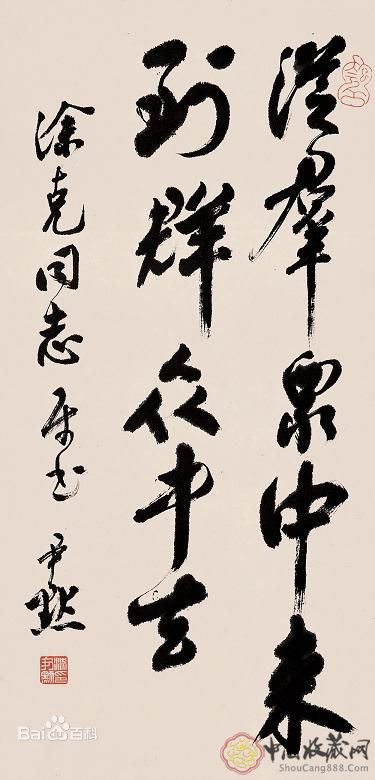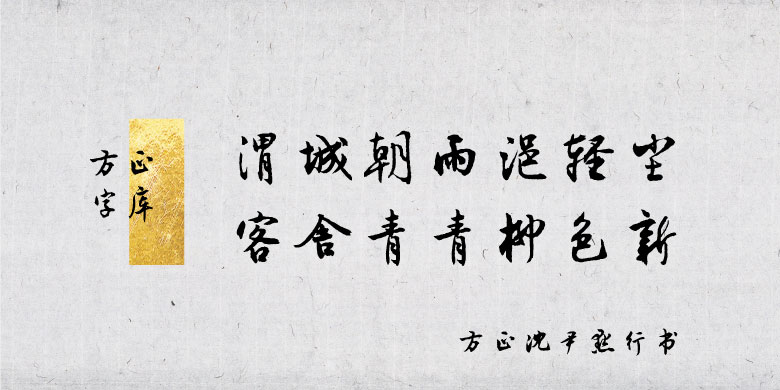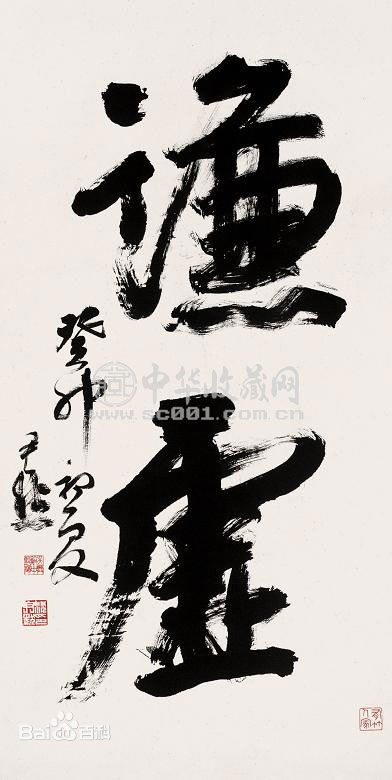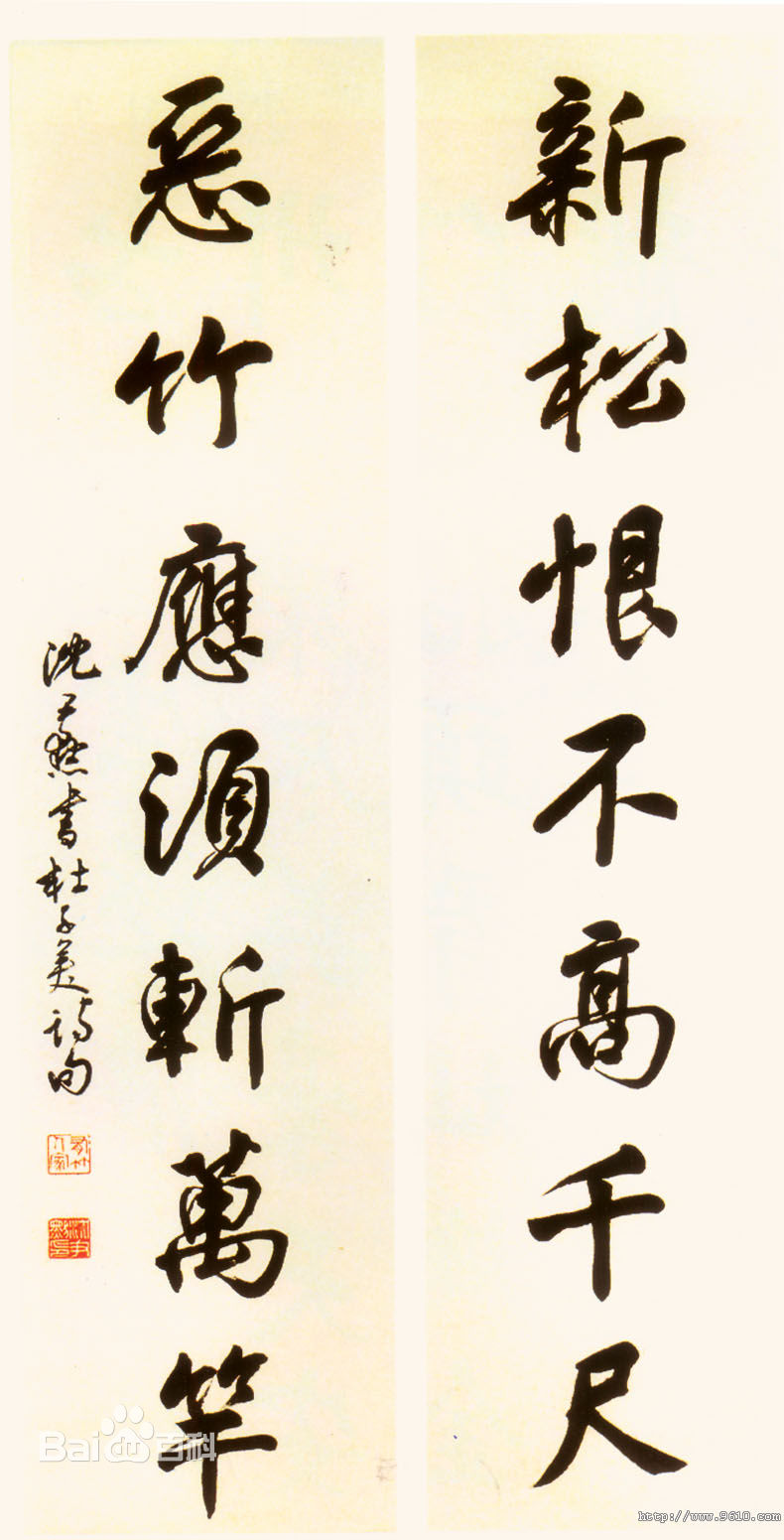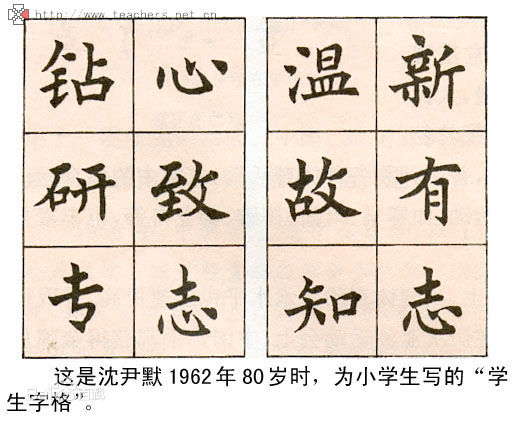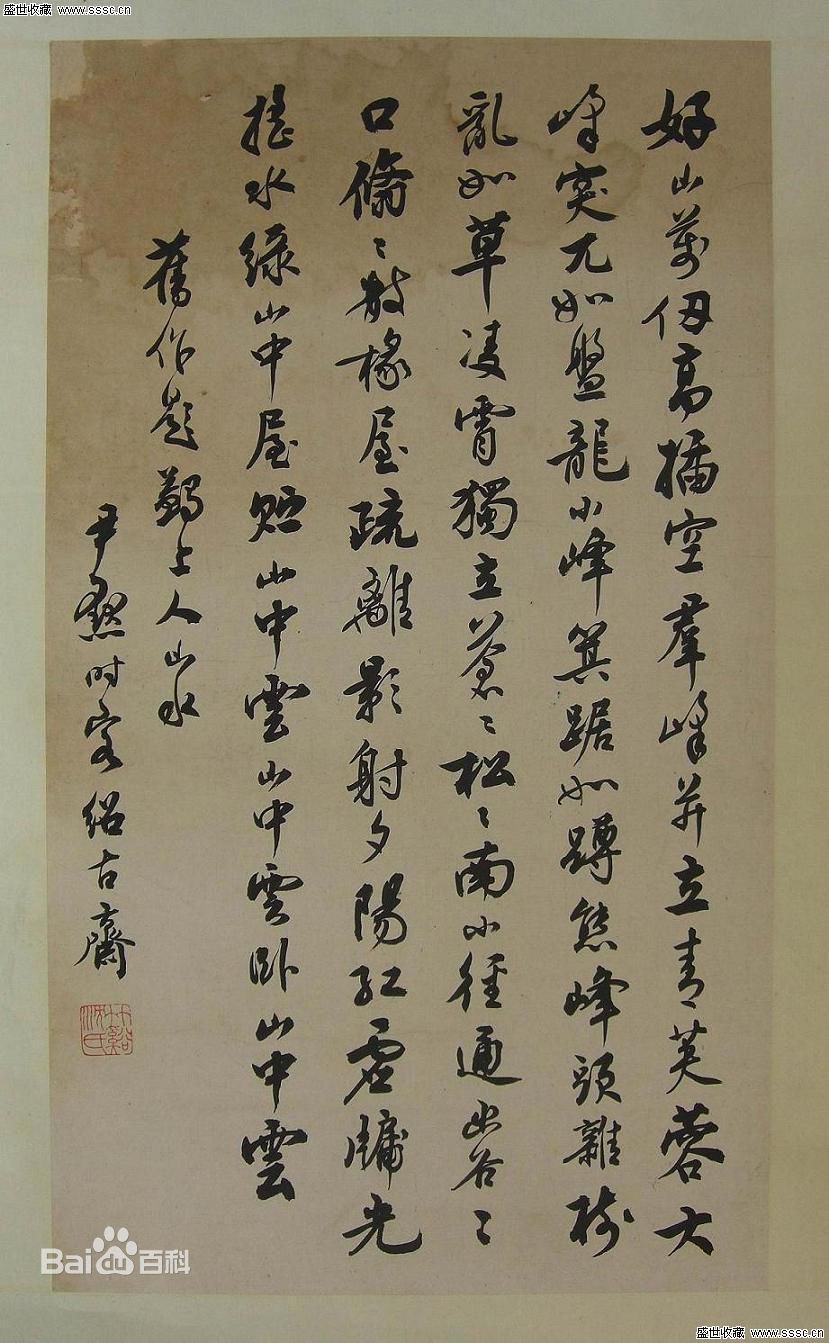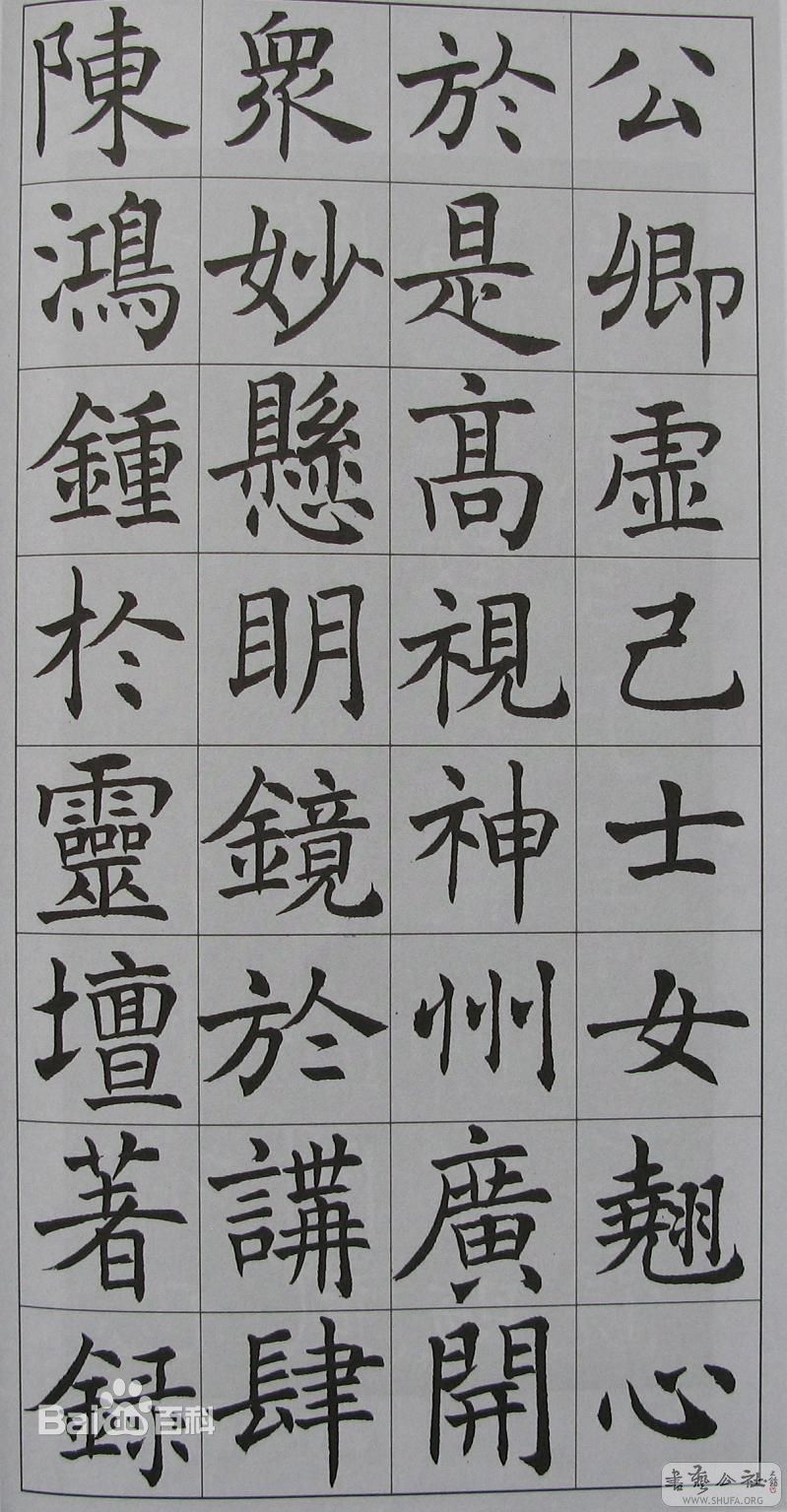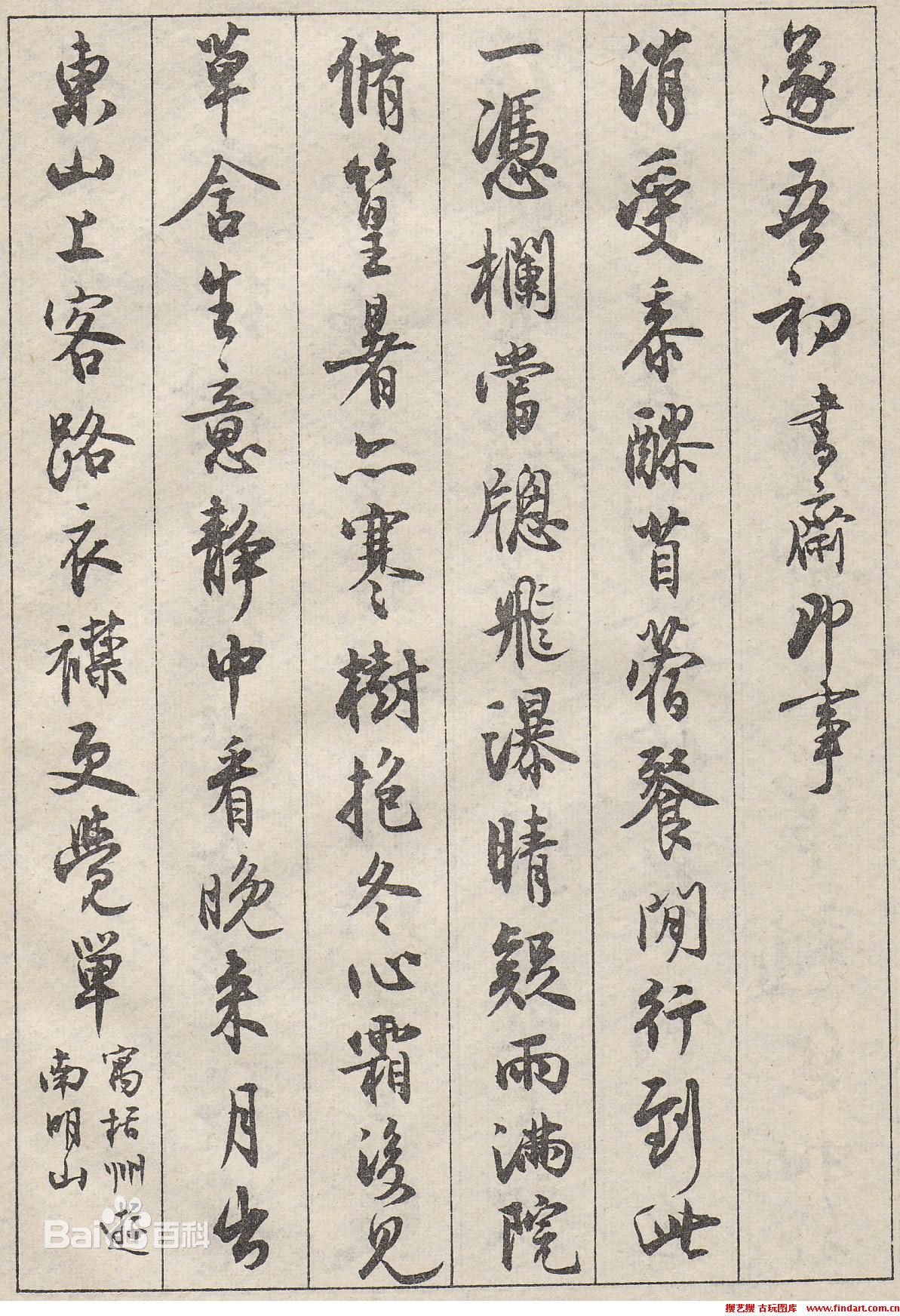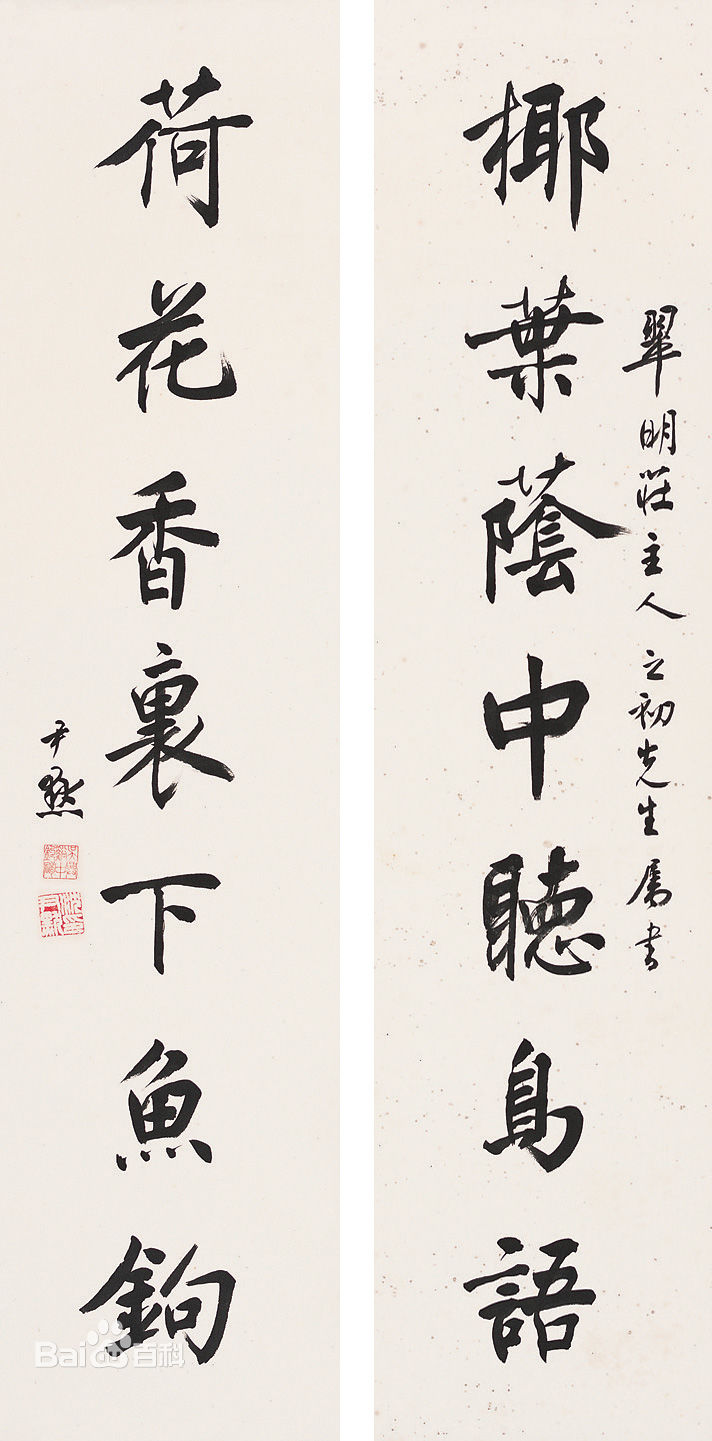
方正沈尹默行书 简
字体介绍:
沈尹默(1883-1971),当代书法家、诗人。原名君默,字中,号秋明,浙江吴兴(今湖州市)人。早年曾留学日本,解放前曾任北京大学文学系教授,北平大学校长。建国后任中央文史馆副馆长等,上海市人民委员会委员,第三届全国人大代表。工正行草书,由以行书著名。初学褚遂良,后遍习晋、唐诸名家,晚年融会苏轼、米芾。精于用笔,清圆秀润中有劲健遒逸之姿。倡导以腕行笔,不主张模拟结构,于笔法、笔势多所阐发,著有《历代名家学书经验谈辑要释义》、《二王书法管窥》、《秋明诗词》等。
字体特征: 以多种沈尹默墨迹为字形依据。笔法挥洒自如,如行云流水,自然流畅。结字跌宕起伏,清健秀雅。既古意盎然又具有中和圆融的独特面貌。
沈尹默(1883年-1971年),原名君默,后改尹默,字中、秋明,号君墨,别号鬼谷子。祖籍浙江湖州,1883年生于陕西兴安府汉阴厅(今陕西安康市汉阴县城关镇民主街),著名学者、诗人、书法家、教育家。
早年留学日本,后任北京大学教授、北平大学校长、辅仁大学教授,《新青年》杂志编委。与兄长沈士远、弟沈兼士合称“北大三沈”。沈尹默1949年后历任中央文史馆副馆长,上海市人民委员会委员,第三届全国人大代表等职务。
沈尹默以书法闻名,民国初年,书坛就有“南沈北于(于右任)”之称。二十世纪四十年代书坛有“南沈北吴(吴玉如)”之说。与李志敏合称“北大书法史上两巨匠”。 [1] 著名文学家徐平羽先生,谓沈老之书法艺术成就,“超越元、明、清,直入宋四家而无愧。”已故全国文物鉴定小组组长谢稚柳教授认为:“数百年来,书家林立,盖无人出其右者”。已故台北师大教授、国文研究所所长林尹先生赞沈老书法“米元章(米芾)以下”。北京大学书画协会会长张辛教授评价:“北大历史上的名书法家只有章梫、金息侯、罗复堪、沈尹默等寥寥几人而已,李志敏是改革开放新时代第一人。”
方正沈尹默行书